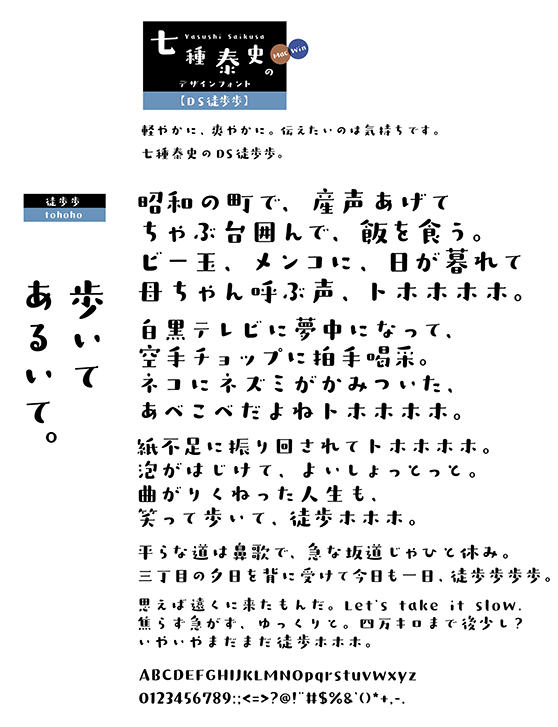
DS徒歩歩 (DS-tohoho)
DS-tohoho
軽やかに。楽しく明るく懐かしく。ゆっくり、ほっこりした書体です。
七種泰史/デザインシグナルの紹介
こころのこもった文字創りを目指す七種泰史氏のオリジナルブランド「デザインシグナル」。2008年夏からスタートし、年に2~3書体のペースで開発を進行中。多くのファンが新作を心待ちにする人気のブランド。